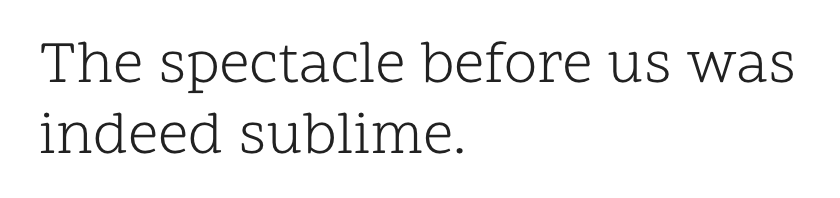
ich habe letztens die von Dalton Maag entworfene Scope One entdeckt, die für Google Fonts entworfen wurde, und ich muss sagen, die gefällt mir sehr gut. Die Rundungen am p z. B. finde ich schön. Leider hat diese Schrift nur einen Schnitt, nämlich Light (s. Anhang) -> https://fonts.google.com/specimen/Scope+One
Ich bin auf der Suche nach einer ähnlichen Schrift, die aber besser ausgebaut sein sollte. Ich hab selbst natürlich auch schon herumgesucht und fand da z. B. die FF Milo Slab ganz passend:
Aber vielleicht kennt ihr noch andere Schriften, die ähnlich sind?
Die Ziffern, das a und die Laufweite erinnern mich etwas an die Museo Slab.
Weitere in diese Richtung:
• Sanchez
• Tabac Slab
• Open Serif
Wenn Dir eher das Verspielte gefällt, könnte Dir auch die FF Suhmo zusagen.
Es sind ein paar tolle Vorschläge dabei. Ich finde alle sehr ansprechend. Aber besonders die Graublau und die FF Suhmo haben es mir angetan ;) Danke.